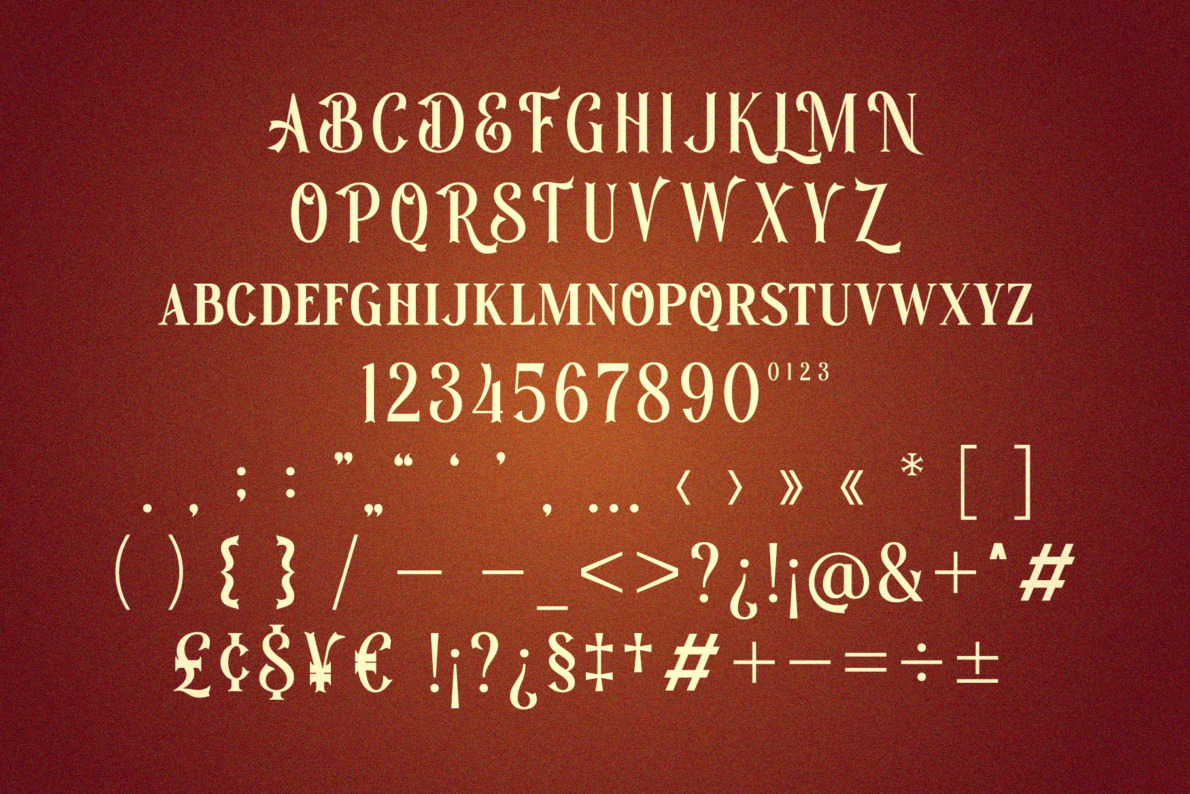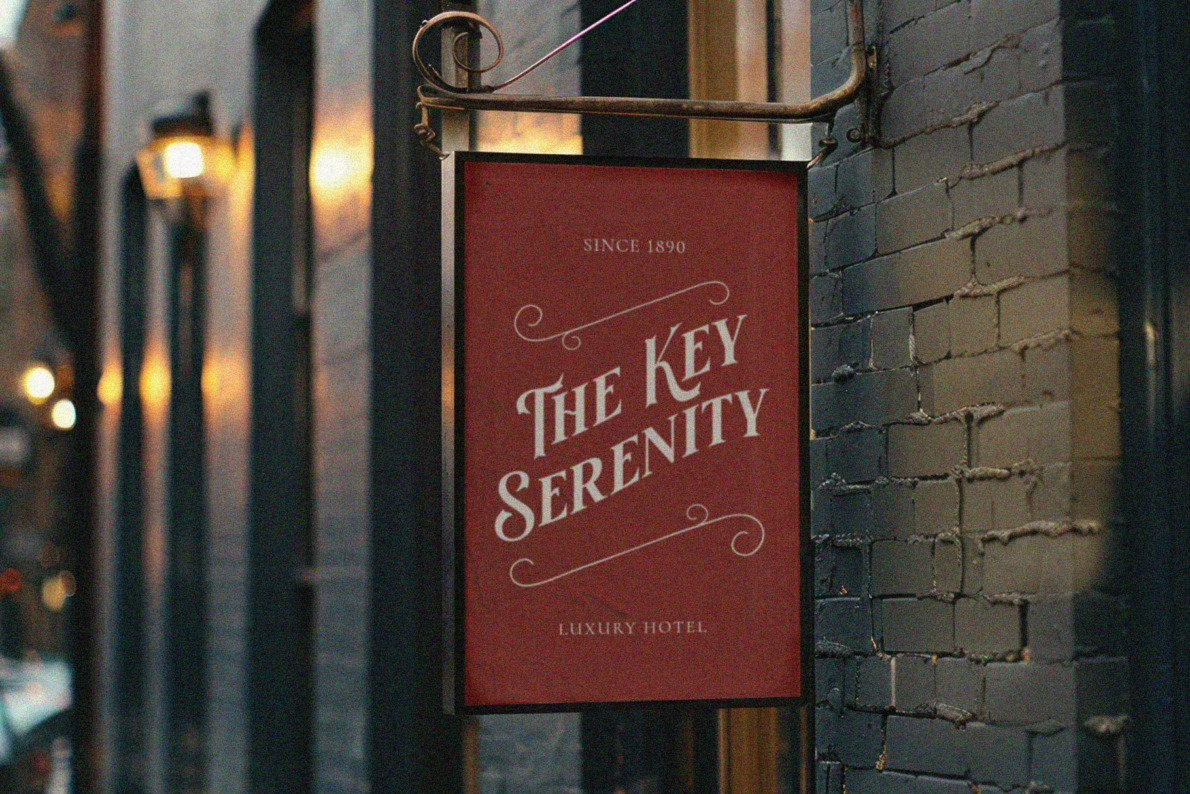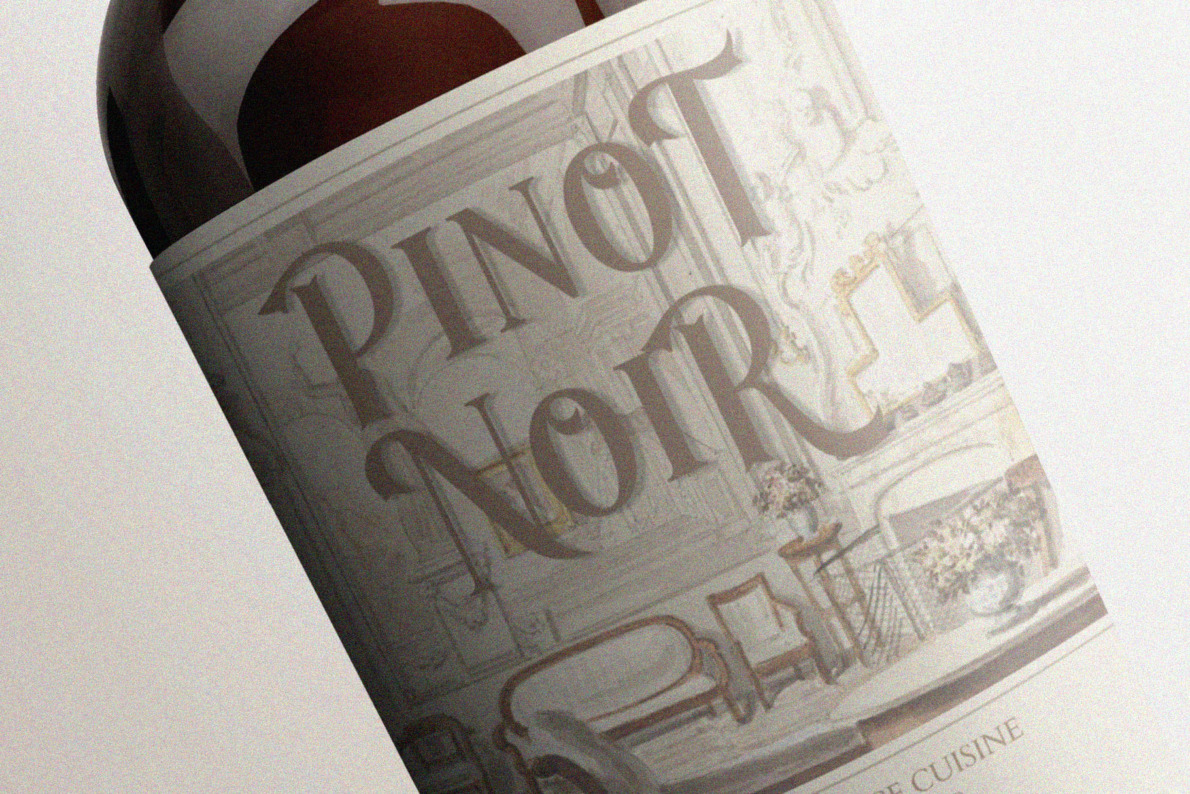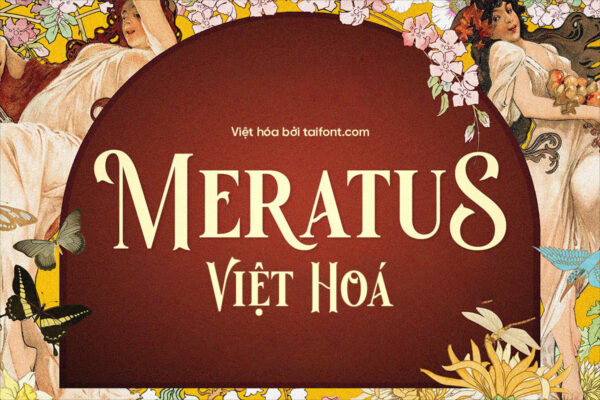
Giới thiệu về Font TF Meratus Việt hóa
TF Meratus Việt hóa là một font chữ nổi bật với thiết kế mang đậm phong cách vintage, cổ điển và đầy sang trọng. Font này toát lên vẻ đẹp của sự hoài niệm, tinh tế và một chút bí ẩn, gợi nhớ về thời kỳ vàng son của nghệ thuật thủ công và quảng cáo xưa. Những đường nét của Meratus thường chắc chắn, có độ dày vừa phải, mang lại cảm giác vững chãi và đáng tin cậy.
Với đặc điểm là phong thái hoài cổ và khả năng truyền tải sự tinh tế, Meratus là lựa chọn hoàn hảo cho các thiết kế muốn thể hiện sự đẳng cấp, sự bền vững và một chút lãng mạn của thời gian:
- Thiết kế tem nhãn rượu: Hoàn hảo để sử dụng trên nhãn chai rượu vang, rượu mạnh hoặc các loại đồ uống cao cấp khác. Font này giúp tạo cảm giác về chất lượng, sự lâu đời và tính thủ công của sản phẩm, làm tăng giá trị cảm nhận cho chai rượu. Nét vintage của Meratus sẽ làm nhãn chai trở nên độc đáo và thu hút.
- Thiết kế bảng hiệu kiểu cổ điển: Lý tưởng cho các bảng hiệu của nhà hàng, quán cà phê, cửa hàng đồ cổ, hoặc bất kỳ không gian nào muốn mang phong cách retro, hoài niệm. Font này giúp tạo không khí chân thực, ấm cúng và đầy tính nghệ thuật.
- Thiết kế bao bì sản phẩm (vintage): Phù hợp cho các sản phẩm thủ công, đặc sản địa phương, hoặc các mặt hàng muốn truyền tải sự tinh tế và câu chuyện về nguồn gốc.
Với TF Meratus Việt hóa, bạn có thể dễ dàng thổi hồn vintage, sự sang trọng và vẻ đẹp cổ điển vào các thiết kế, tạo ra những sản phẩm không chỉ đẹp mắt mà còn đầy cảm xúc và chiều sâu.
Font Việt hóa TF Meratus – Phong chữ Thiết kế rượu, bảng hiệu cổ điển